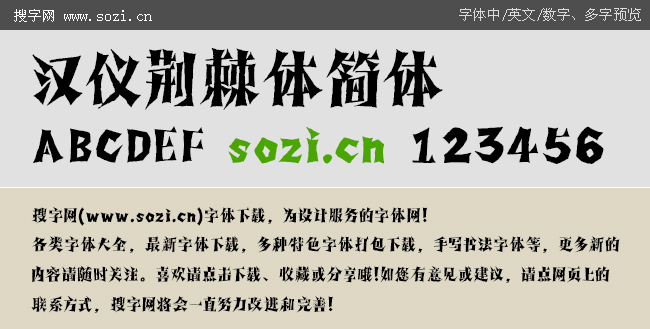
漢儀荊棘體簡體
搜字網(wǎng)給大家提供一款漢儀荊棘體簡體中文字體下載,漢儀攀登者簡體是一套廣告POP字體,筆畫書寫中粗細(xì)不一,筆畫上像是長有參差不齊的荊棘,字體效果效果非常的不錯,非常有趣味性。適用于畫冊設(shè)計、海報設(shè)計、包裝設(shè)計等場合使用。(本字體為個人非商用版,如需要商用請聯(lián)系漢儀公司購買版權(quán))